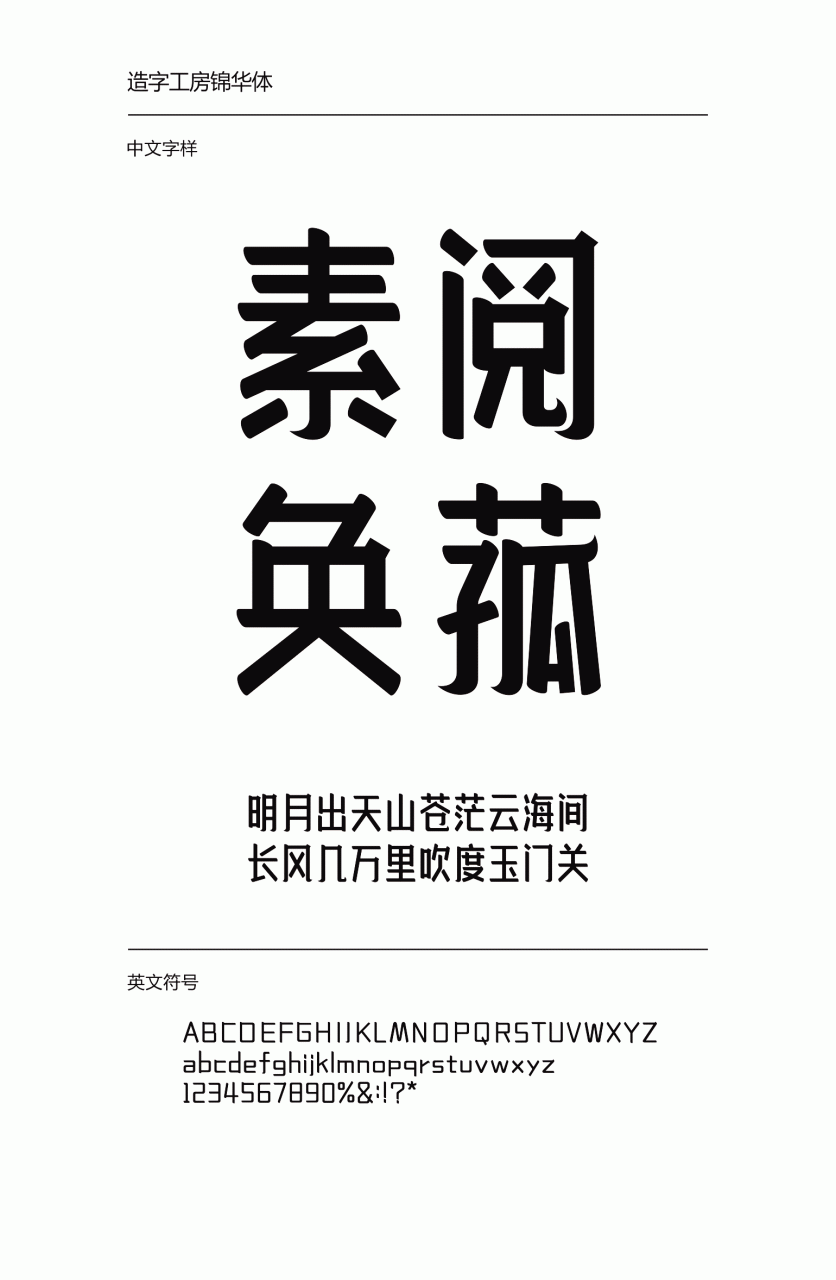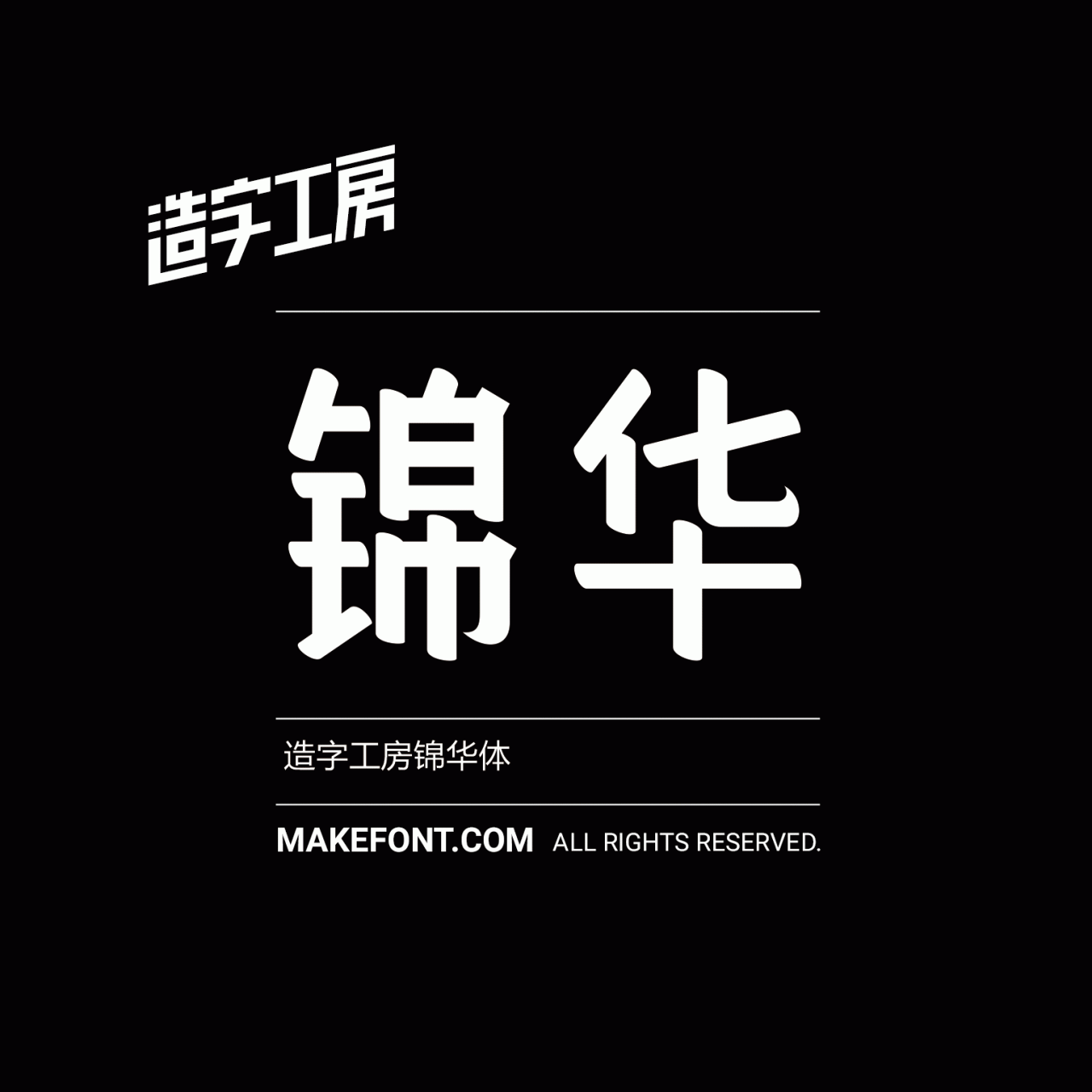
造字工房锦华体,其字形瘦长,隽永俊秀、清新率真,勾画的处理拙中见巧,不失活泼。风格朴实敛静、简淡秀润中又不失坚韧,适用于大标题及个性品牌设计推广等环境。本字体为简体字库,采用OpenType/CID格式,Adobe-GB1-5编码。基于中华人民共和国GB2312-80字符集标准,另按需添加101个汉字。共收容字数6864CJK汉字,ASCII常用字符100个。